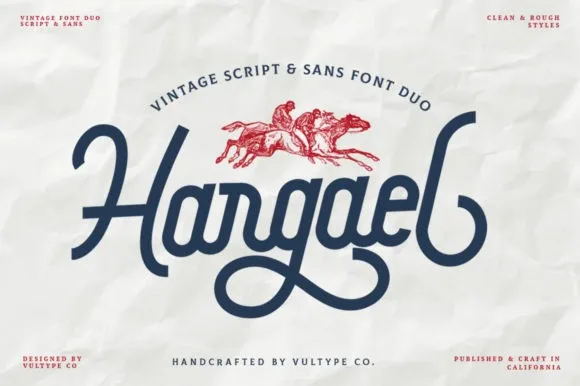
Hargael – Vintage Script Font – Download Grátis
Esta é uma fonte Vintage Script que vem acompanhada de uma combinação de tipo sans-serif e moderno script. Com ela, você pode facilmente realizar todos seus ideais gráficos. Introduzimos Hargael Font Duo . É um duo de fontes impressionante que contém um tipo de script e tipo sans-serif. Seus belos suaves são inspirados por tudo antigo. A fonte vintage Hargael Script, se alia perfeitamente e é ideal para criar logotipos tradicionais, etiquetas, embalagens de produtos, letras em camisetas e muito mais. É uma combinação única que traz elegância à sua identidade visual. Seja você criando um logo para uma marca ou buscando personalizar a aparência de suas peças de moda, Hargael Font Duo é perfeito para todos esses propósitos. A fonte vintage Hargael Script dá um toque vintage ao seu design sem tirar o foco do estilo moderno, criando um efeito arrebatador que vai impressionar seus clientes.